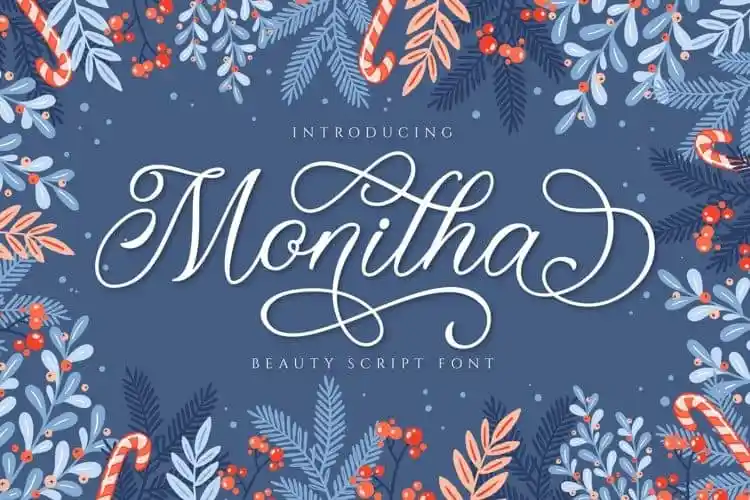
Monitha Calligraphy Font – Fonte Grátis
Monitha Calligraphy Font
A Monitha Calligraphy Font é uma elegante ferramenta para designers que desejam trazer um toque pessoal a seus projetos gráficos. Manufacturada por ToniStudio, esta fonte foi meticulosamente criada com a intenção de torná-la uma escolha favorita. Ela adquire vida e originalidade em aplicações variadas como convites de casamento, cartões de gratidão, frases motivacionais, cartas de cumprimento, logomarcas ou até mesmo cartões de visita. Sua beleza perfeccionada torna-a uma escolha imperdível para qualquer projeto que se destine a um toque pessoal e encantador. Com sua Monitha Calligraphy Font, você pode criar mensagens memoráveis com um toque único que certamente impressionará seus leitores.